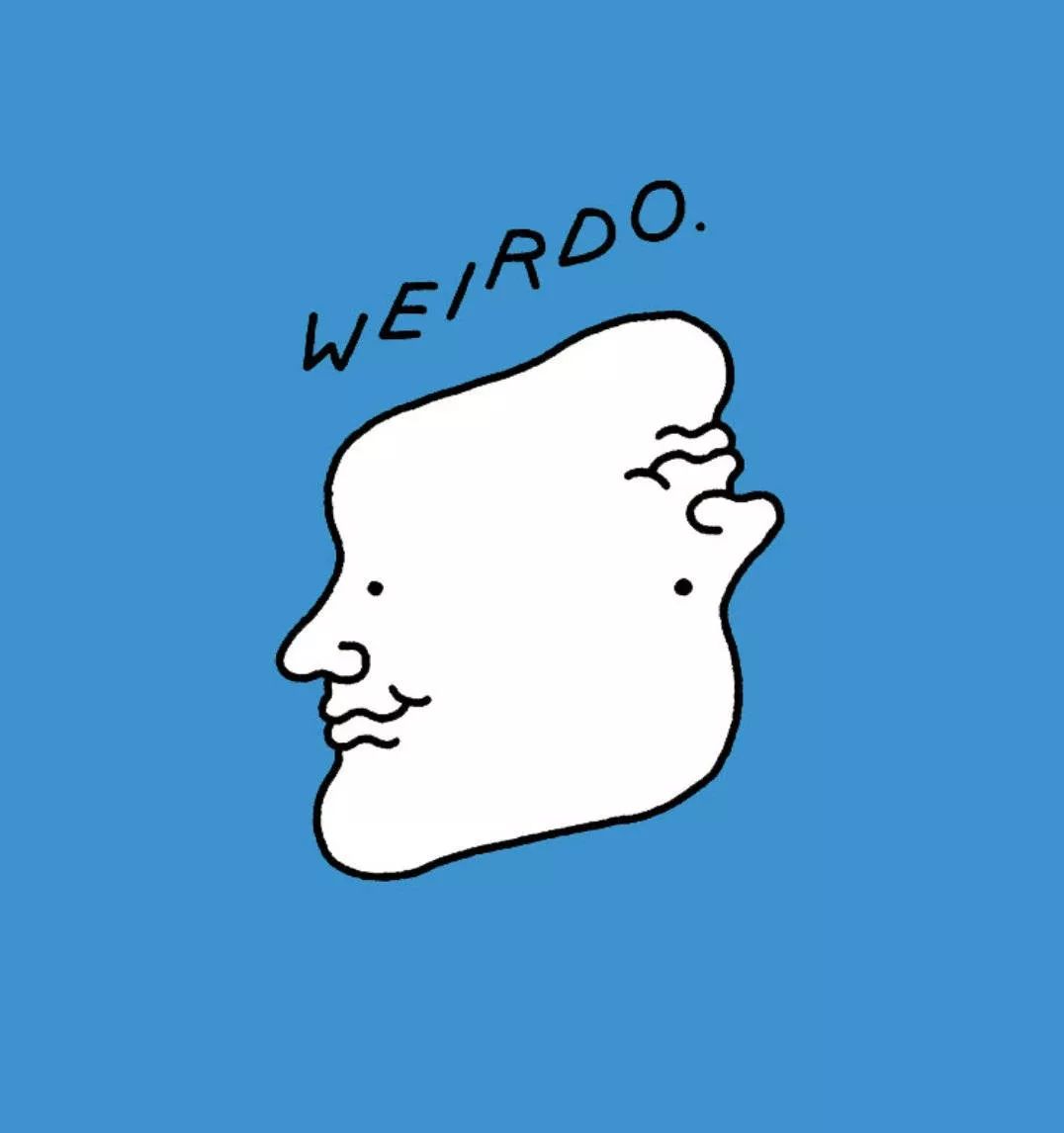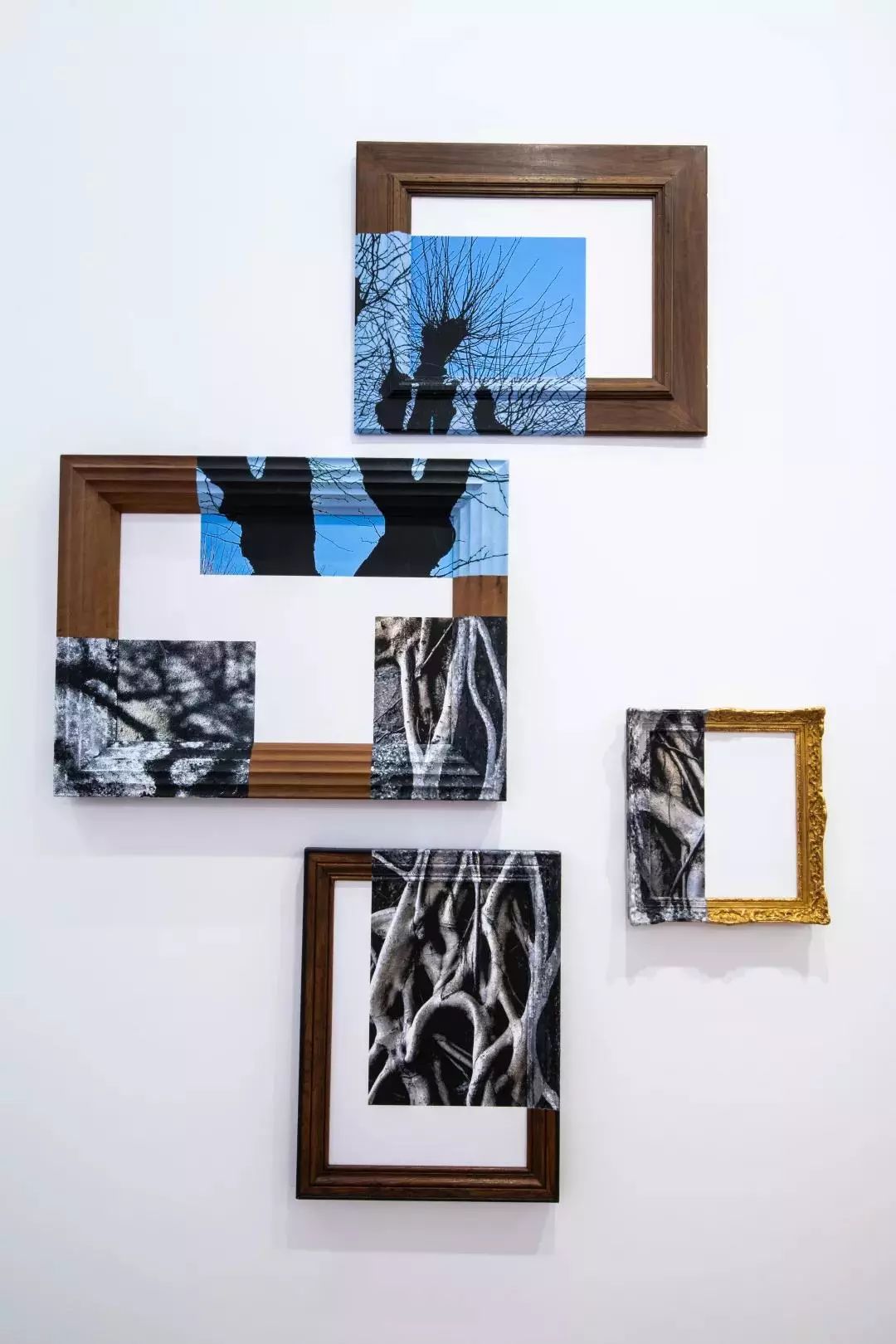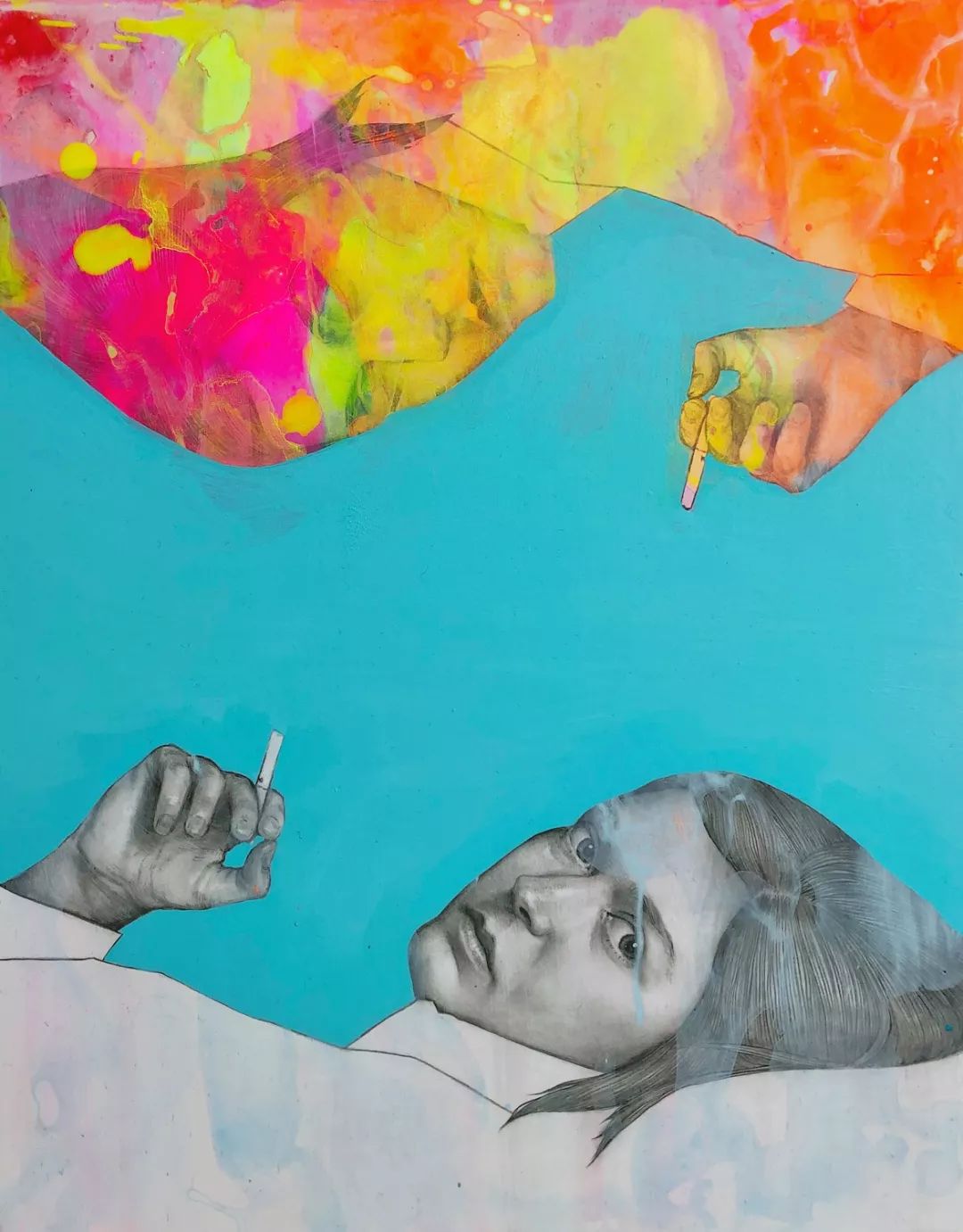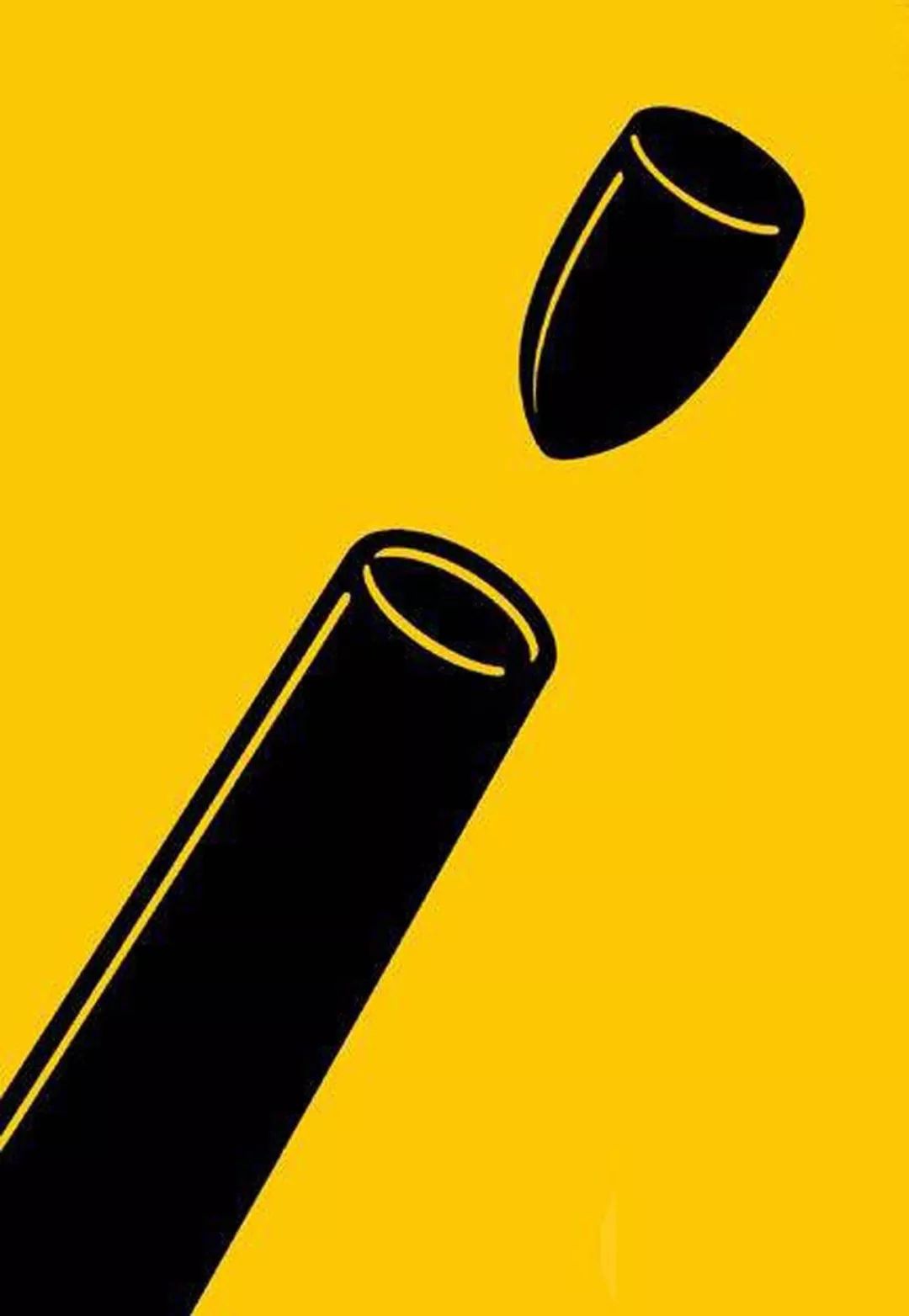
猫爪杯火爆的背后,你缺的不是钱,而是这种硬实力
这几天柚子一直在思考一个问题,素材可以下载,海报可以模仿,鹿班甚至可以取代设计师,那10年、20年后,你还凭什么养活自己?这个话题有点深,感觉给自己挖了个大坑,但我也心甘情愿地跳~
这两天超火爆的猫爪杯都知道吧,已经炒到上千,还闹出打架事件……除了戳中了“猫奴”的心理,在设计上跟以往的也不一样,特别是倒上牛奶的样子,简直是颜值爆表~
那么问题来了,为什么宁愿花上千买猫爪杯,也不愿买一只真猫回家撸到掉毛?
还不是因为它跟你想象中的不一样,一般的杯子,都是在底部做变化,或者杯身的图案,而星巴克这款,是杯中杯,制造往里伸的视觉效果,小肉垫能360度无死角,当然看得一众铲屎官心花怒放~
就为了这独一无二的颜值,挤破头、钱包空也在所不惜,我不想去深究这背后到底是饥饿营销,还是中国人喜欢跟风。但有一点,作为设计师,你必须要学习的,那就是逆向思维。
你懂逆向思维吗
什么是逆向思维?应该不用我多说,一张图就能解释。
但我想说的是,每个人不是只有一个影子,还有多重人格,逆向也不只是倒推顺向,而是多角度出发。
所有你看到的、听到的、说到的、摸到的、想到的、感觉到的,都是你的灵感来源。
比如耐克,印象中就是一个大√,可当它反过来,却有意想不到的视觉冲击力。
你焦虑发际线退后,头发越来越少,反过来想不就豁然开朗吗?
还有不被方框限制住,不停地打破、重组~
这个鱼缸是不是似曾相识,感觉猫爪杯都采集了它的灵感。
看我反着逆
先从最简单的开始,看惯了的轨迹,突然反着来,是不是有点新鲜~
日本设计教父福田繁雄的作品,你一定看过。
还有《Dark Tower》的电影海报,感觉有点像盗梦空间,换个角度看世界。
还有下面这些“倒行逆施”的设计,你可以慢慢感受~
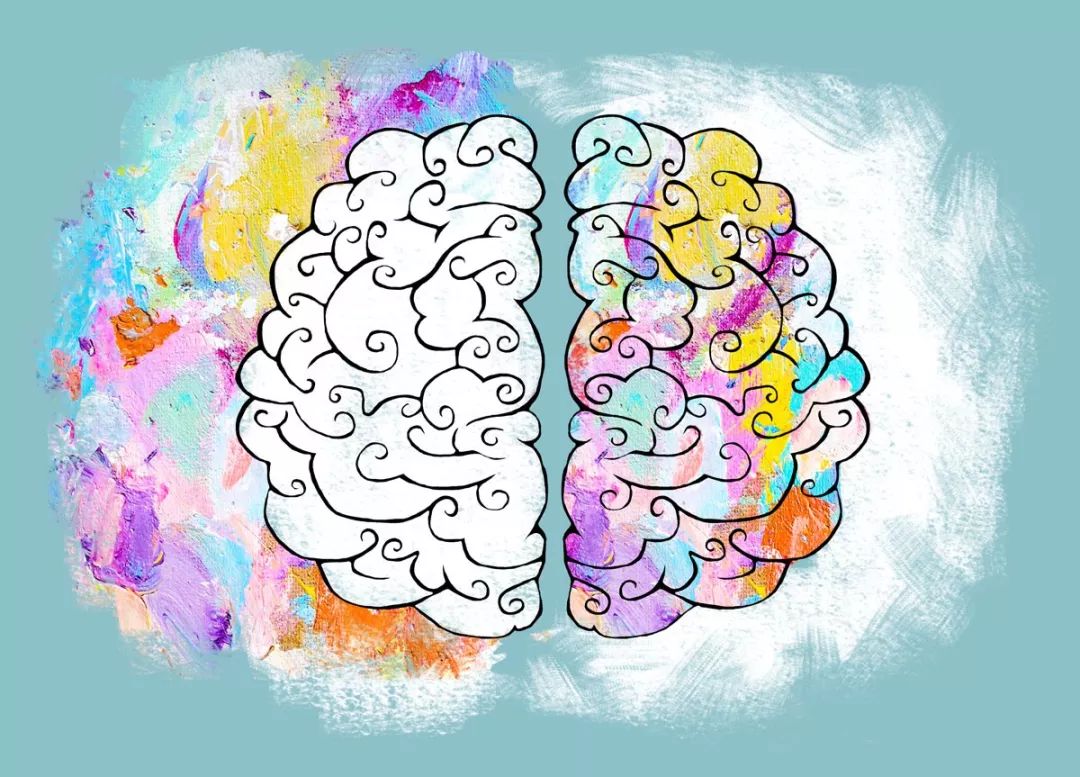
看我放大逆
前面也说过,逆向思维不止一种,最直观的是反着来,还有一种放大局部,看黄海的设计就知道了。
所以在设计中,你也可以放大细节,好比这个38女神节,你会想到在8上做文章么?
也可以在字母上做文章……
小时候周二一看电视就这样,想过放大后的效果吗?
同一个画面中,制造反差。
也可以多几个局部,带给人空间想象力。
或者把重点文字放大。
感觉这个也可以做《绿皮书》的海报呢,哈哈哈~
最喜欢这张,把大白的感觉都“挤”出来了。
看我单独逆
上学的时候,只要是不听从大部队指挥的,都被会老师评为叛逆分子,而现在这种不随大流的独特个性,越来越稀缺,因为太扎眼。
看我交叉逆
这种你一定见过,故意制造交叉重叠,让画面看起来跟死板无缘。
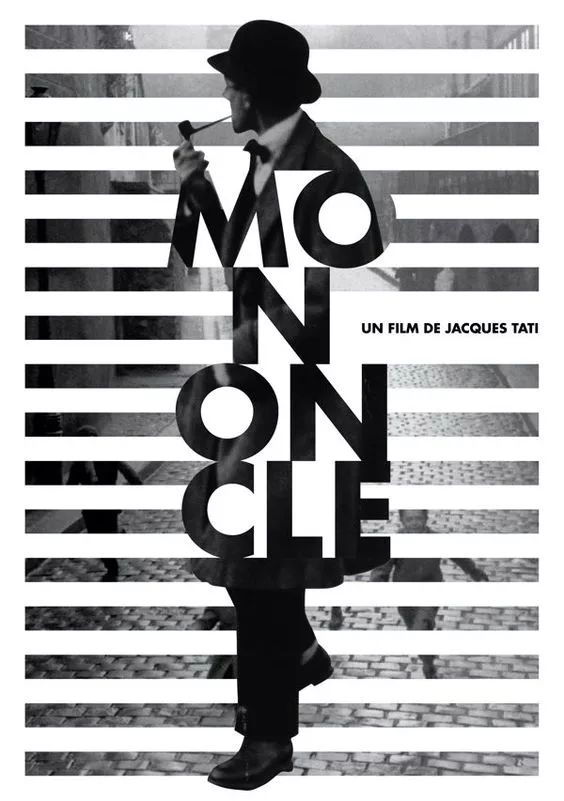
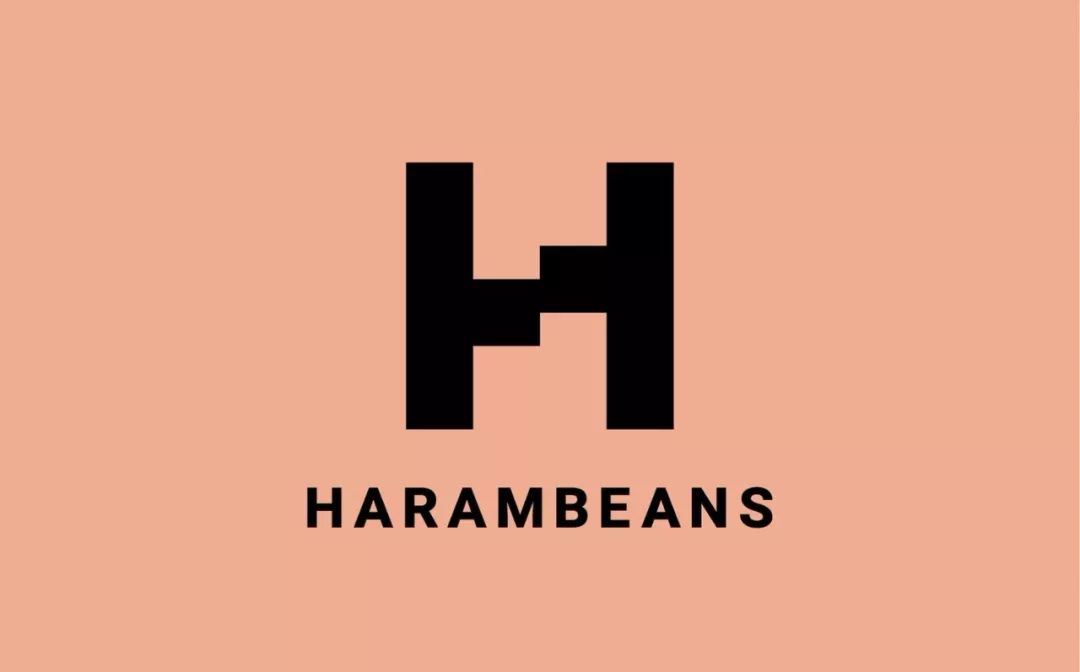
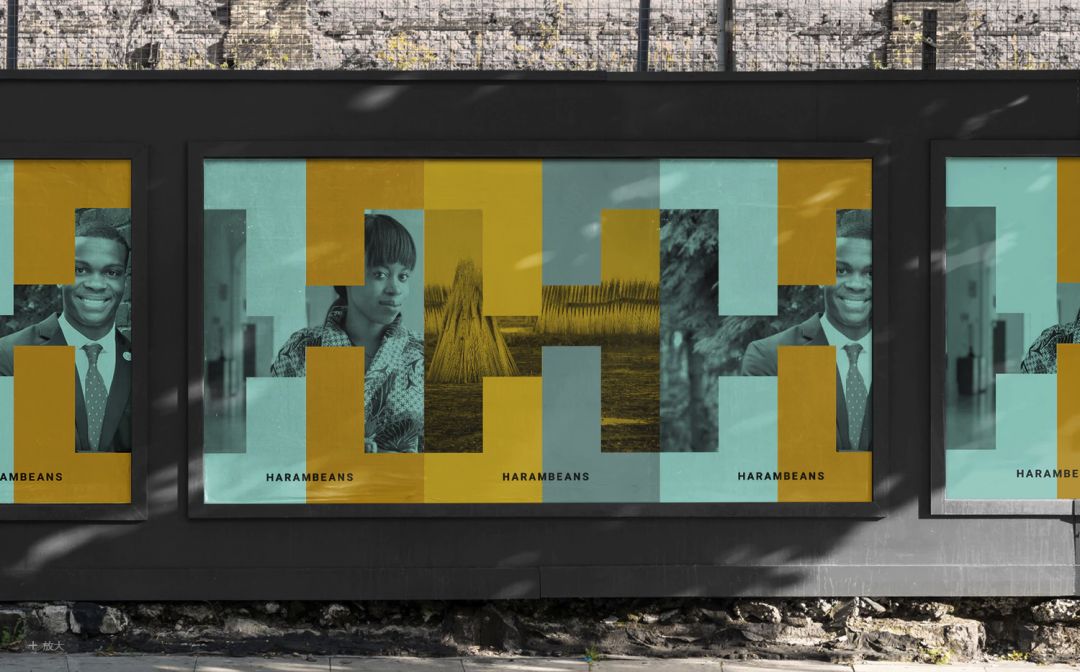
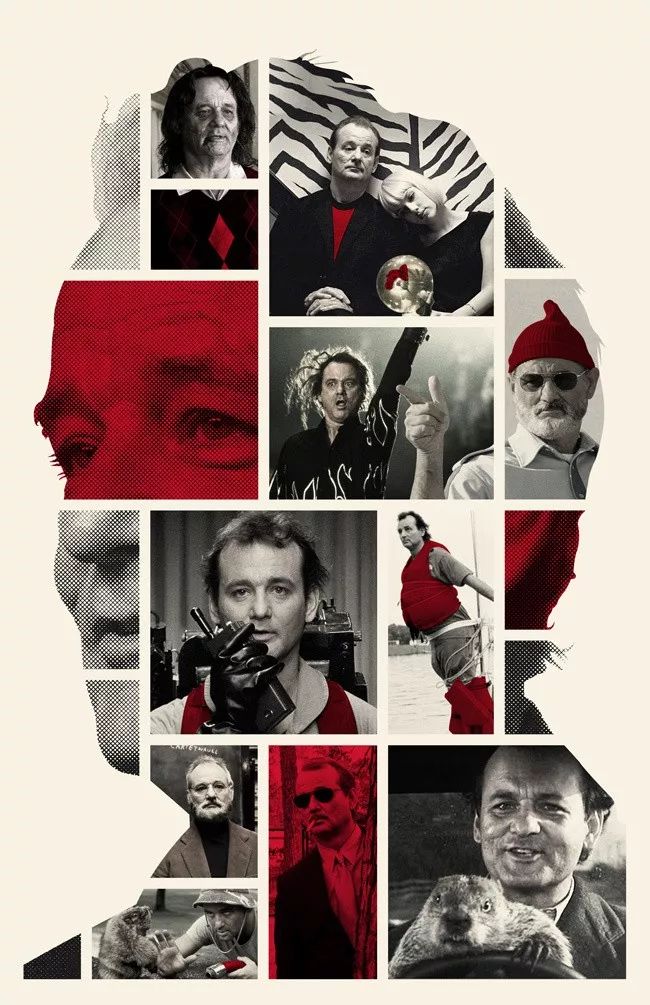
看我替换逆
之前微博发过一组动图,很开脑洞,把字母替换成场景,就属你会玩~
也发过这个图,用日语替换成指针。
所以你还会怎么举一反三?
每天做功课
其实今天说这么多,也主要是想启发你的思考,毕竟一张图,一千个人都有不同的看法,而你能看出跟别人不一样的地方,就是创新。以后记得每天像吃饭一样,做逆向思维训练,比如为什么获得奖牌,就要高兴,不可以倒过来吗?
为什么文字,就得静若处子,不能动如脱兔?
为什么我们就得三点一线的生活,不能打开牢笼呢?
最后,希望你的灵感之光,每天都是亮着的,自己当自己的充电宝。